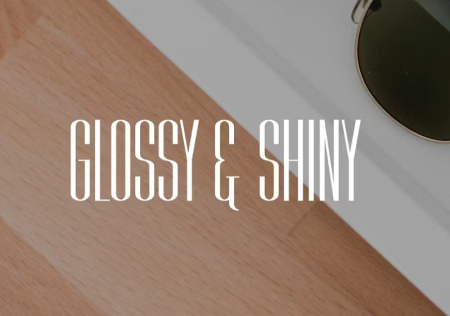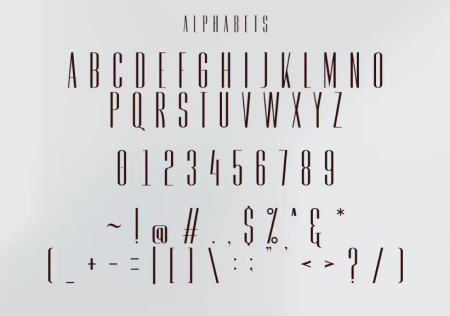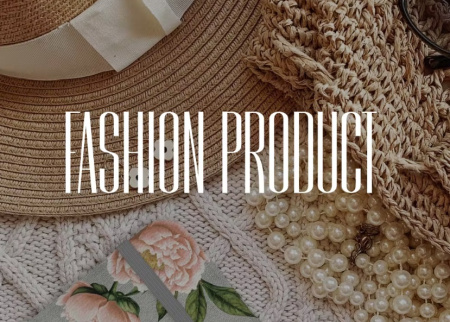
دانلود فونت انگلیسی Machiville مناسب برای استفاده در دنیای مد زنانه. زیورآلاتی مانند کیف، کیف، کفش زنانه، عینک، کیف، مجله ها. شما می توانید در طراحی های مختلف از این فونت انگلیسی زیبا استفاده نمایید. این فونت با فرمت های Otf. و Ttf. ارائه شده است. برای دانلود این فونت از جی اف ایکس دانلود در ادامه مطلب با ما همراه باشید.
دانلود فونت انگلیسی لوکس و زیبای Machiville